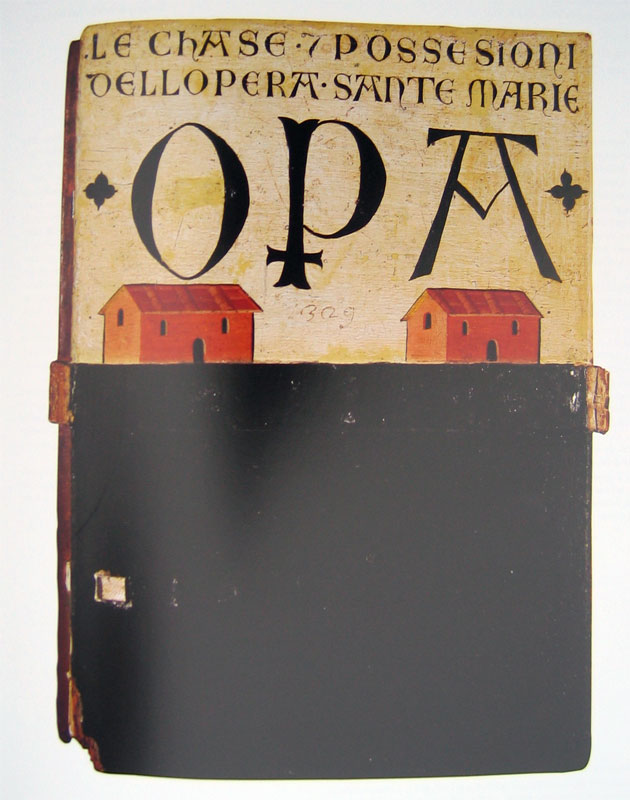
C'est une jolie histoire.... celles des bicchernes* de Sienne :...qui commence en l'an 1257, lorsqu' un magistrat de la ville en charge de l'administration comptable et marchande demande à un peintre de décorer la reliure qui regroupait 6 mois de comptes en liasses. Ce qui fut fait, illustrant donc un moine feuilletant son livre de comptes. Or, à cette époque les reliures de volumes épais étaient en ais de bois (planches), surfaces familières aux peintres.
Le résultat dût satisfaire le besoin de faste confirmant la puissance des dirigeants de la ville et l'opération fut reconduite systématiquement jusqu'au début des années 1600. Soit près de 700 œuvres.
Si au début le thème représenté a peu varié, au fil du temps les peintres ont illustré des évènement locaux : venue d'un ambassadeur, construction nouvelle, etc. Les bicchernes nous fournissent ainsi déja des informations historiques précieuses.
Mais de plus, les artistes se faisant payer leur travail, se retrouvent dans les lignes de comptes ! et c'est la trace de leur activité de telle à telle année, autres infos bien intéressantes notamment pour les peintres mineurs dont on sait peu de choses. Sachant que de "grands" artistes de l'époque ont aussi illustré ces bicchernes.
À partir de 1450 environ, le principe de base du biccherne à été victime de sa réussite, l'aspect ostentatoire a primé et la peinture d'illustration fut désormais faite sur un panneau encadré, indépendant de toute reliure, et du coup, le format vertical imposé par le papier a été souvent abandonné au profit d'un format horizontal.
Cette collection unique a été dispersée, mais les archives de Sienne en possédent 105, après en avoir racheté quand l'occasion se présentait.
Outre la beauté et le caractère unique de cette aventure, c'est aussi la démonstration que, pendant une brève période, le livre et le tableau ont été jumeaux, en supports et en techniques, on trouve des décors en reliefs sous la couche de peinture comme sur le cuir, l'emploi de l'or est identique, etc. Et les peintres savaient drôlement bien manier le dessin de caractères et le ductus !
Voilà, très résumée, l'histoire des bicchernes de Sienne. *Une des étymologies possibles serait "Bücher" : livre Passez tous une très bonne fin d'année, Sabine.